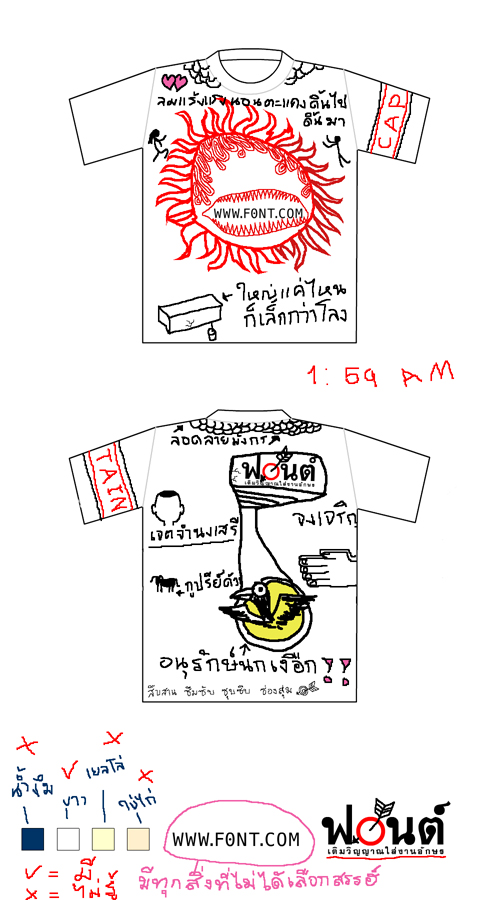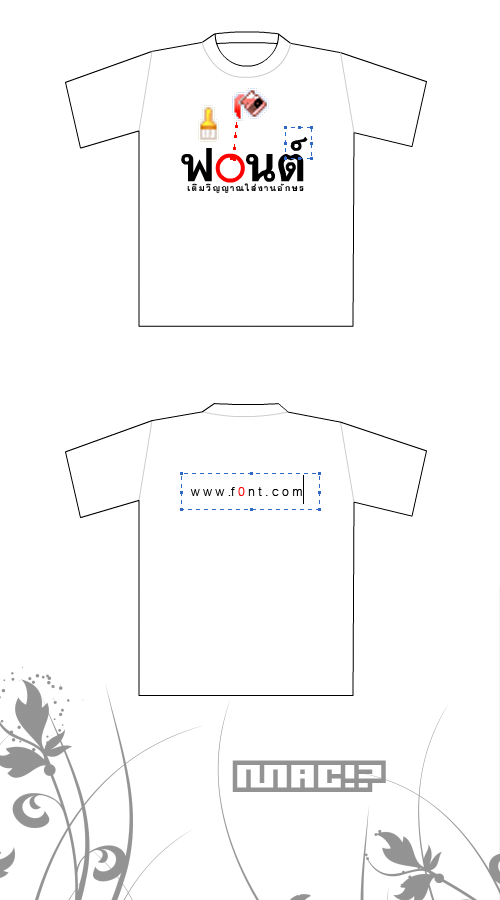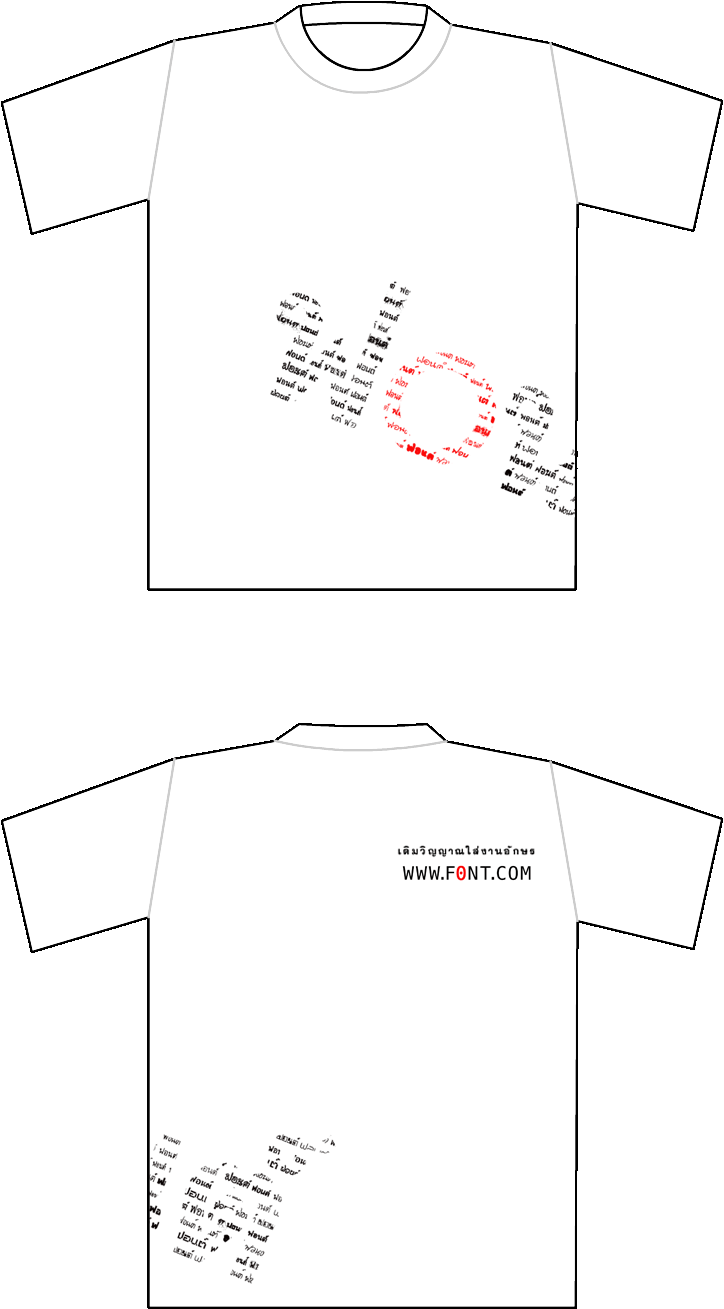
FC7 : เสื้อฟ๐นต์ ภาคสooง
มั่วๆ ครับ  :42:
พี่สาวอรบอกว่า เสื้อเอที่เป็นปีกนางฟ้าสวยมากค่ะ ฮี้กับๆ  :25:
แบบล่างสุด โอ มากเลยครับ
Paint Paint Paint :08:
ลายบรัชข่างล่างน่าสนใจดีครับ
ไม่ลองเอามาออกแบเสื้อหน่อยหรือ ครับ
ชอบของพี่วาฬปีศาจ  :30: :30:
ความจริงมีอีกอันนึง ทำตอนแรก แต่มันรั่วไปหน่อย
ชอบๆ โหวตๆ แต่เอาจริงต้องเพ้นเป็นตัวๆไป :12:
เพิ่งเห็น  :12:
เอาวะ นั่งทำเมื่อกี้ เพิ่งกลับมาจากชลฯ :16: เดี๋ยวต้องขึ้นกรุงเทพต่อ